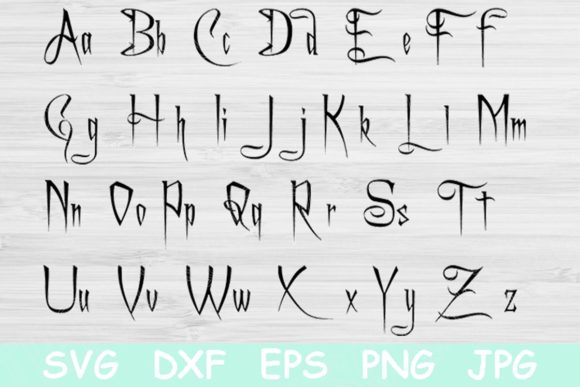
Letter Fonts Svg Script Vine Digitial.
Conçu avec précision, Letter Fonts Svg Script Vine Digitial. offre des vecteurs nets, une typographie fluide et une licence commerciale pour une tranquillité d'esprit.